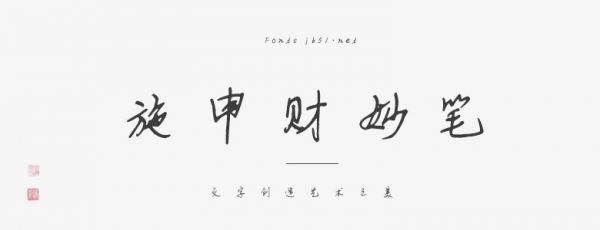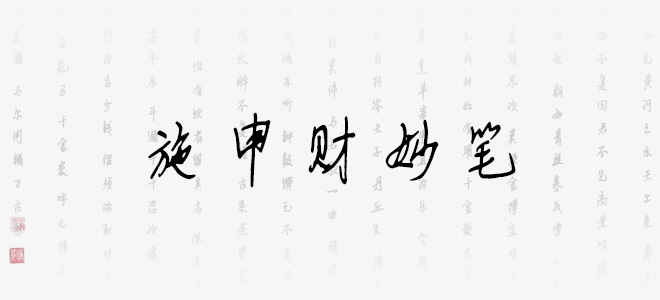
施申財(cái)妙筆是一款手寫藝術(shù)字體,字體線條粗細(xì)適中,筆畫隨性,結(jié)構(gòu)灑脫自在,具有很好的視覺感,適合于文化類的宣傳設(shè)計(jì)、商業(yè)類品牌的廣告和產(chǎn)品包裝設(shè)計(jì)以及個(gè)性化文字排版等較多場景。
施申財(cái)妙筆